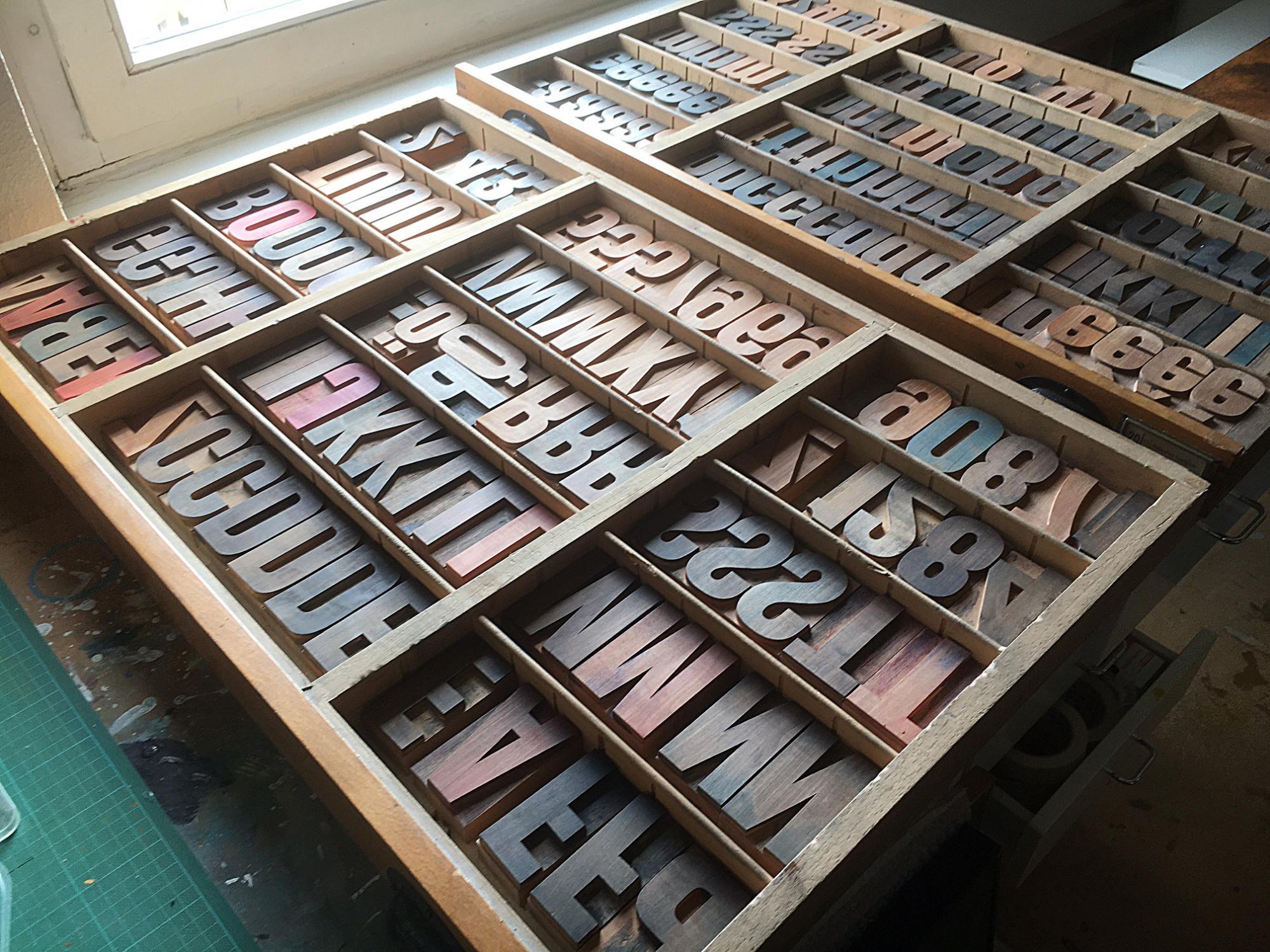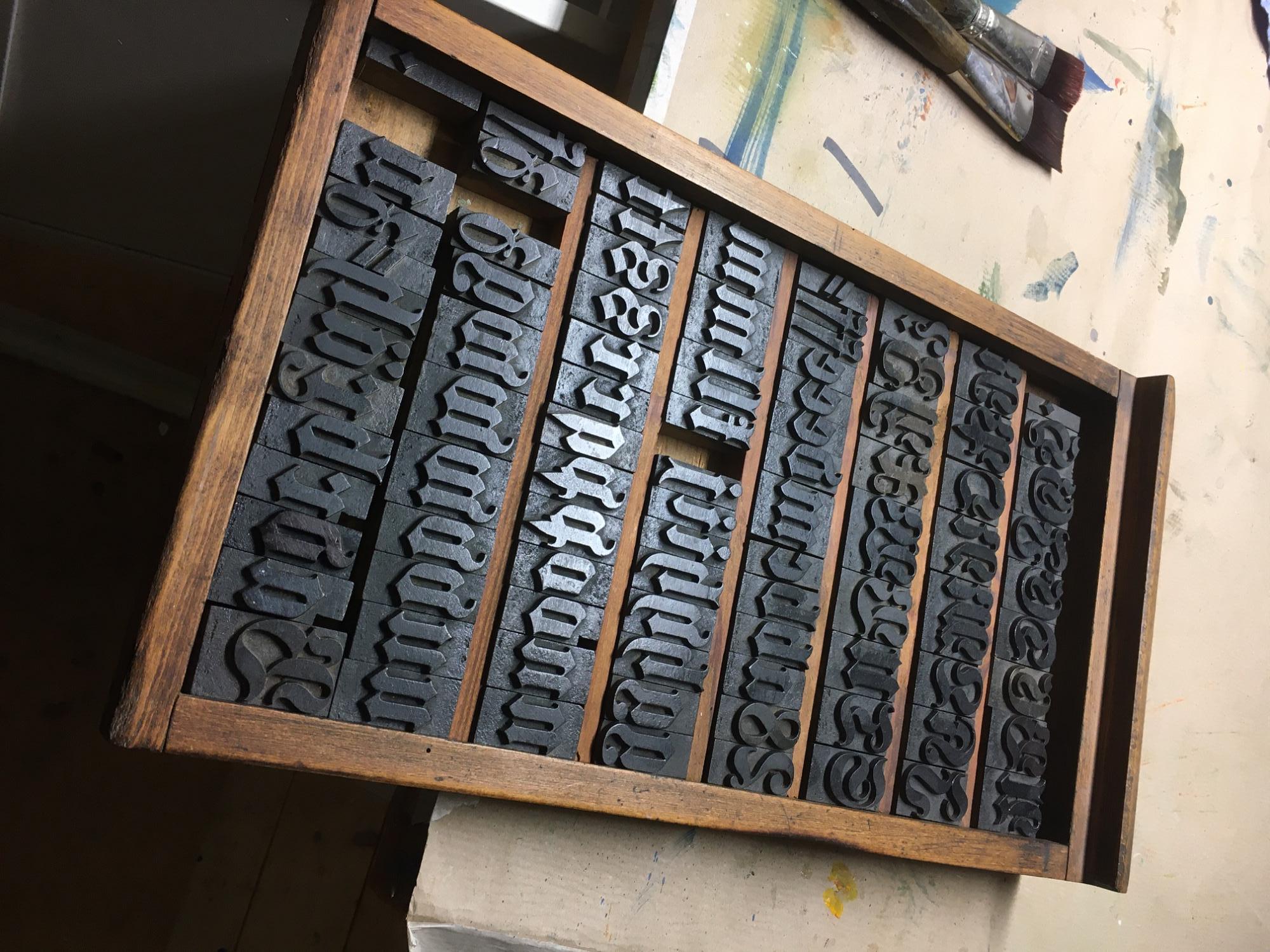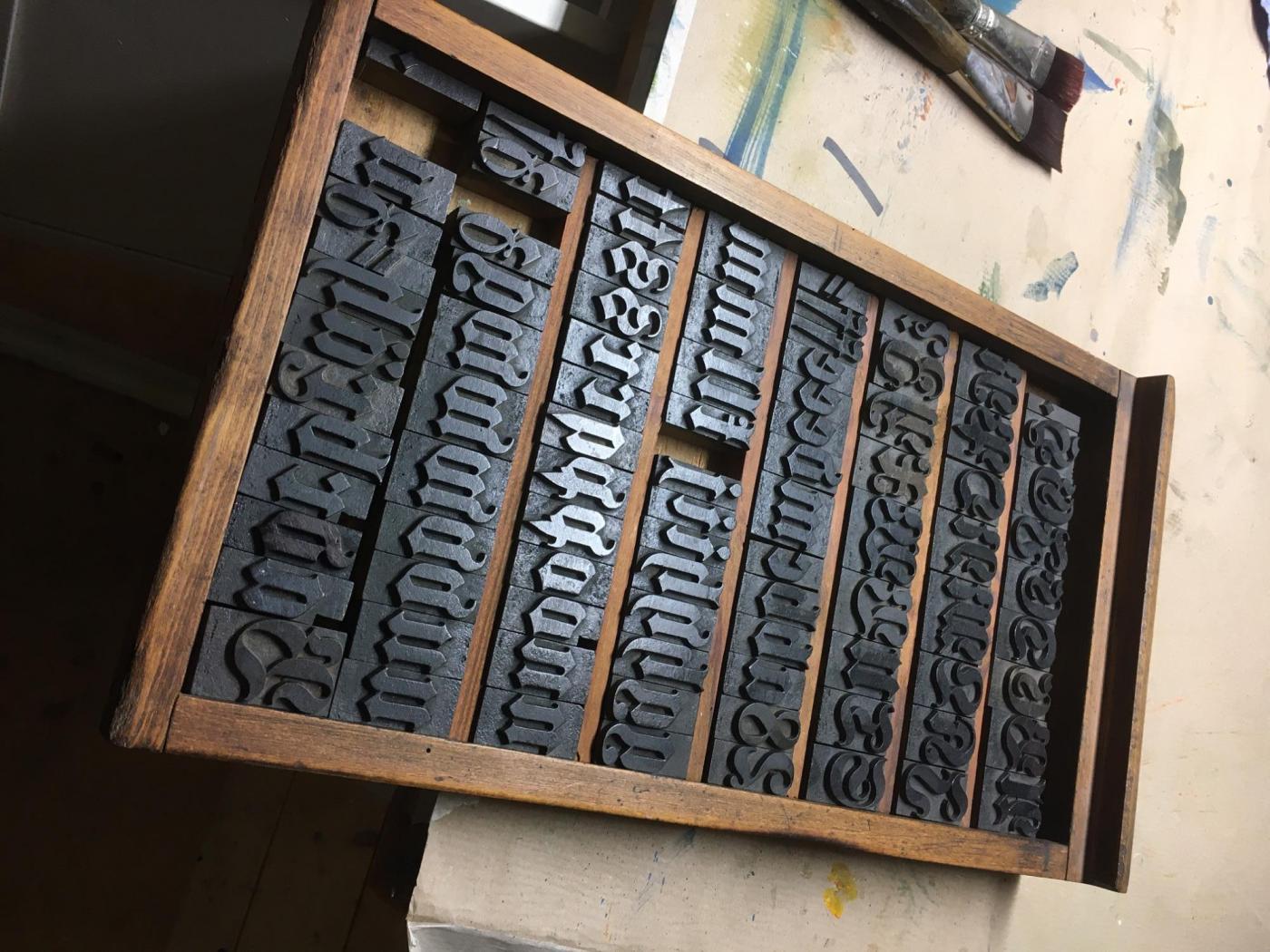
Holzlettern zu verkaufen
Helvetica halbfett, 5 Konkordanz, sehr gut erhalten, teilweise unbenutzt
Helvetica halbfett, 3 Konkordanz, sehr gut erhalten, Versal B und C fehlen leider
Fraktur, 10 Cicero, "antik" aber druckbar